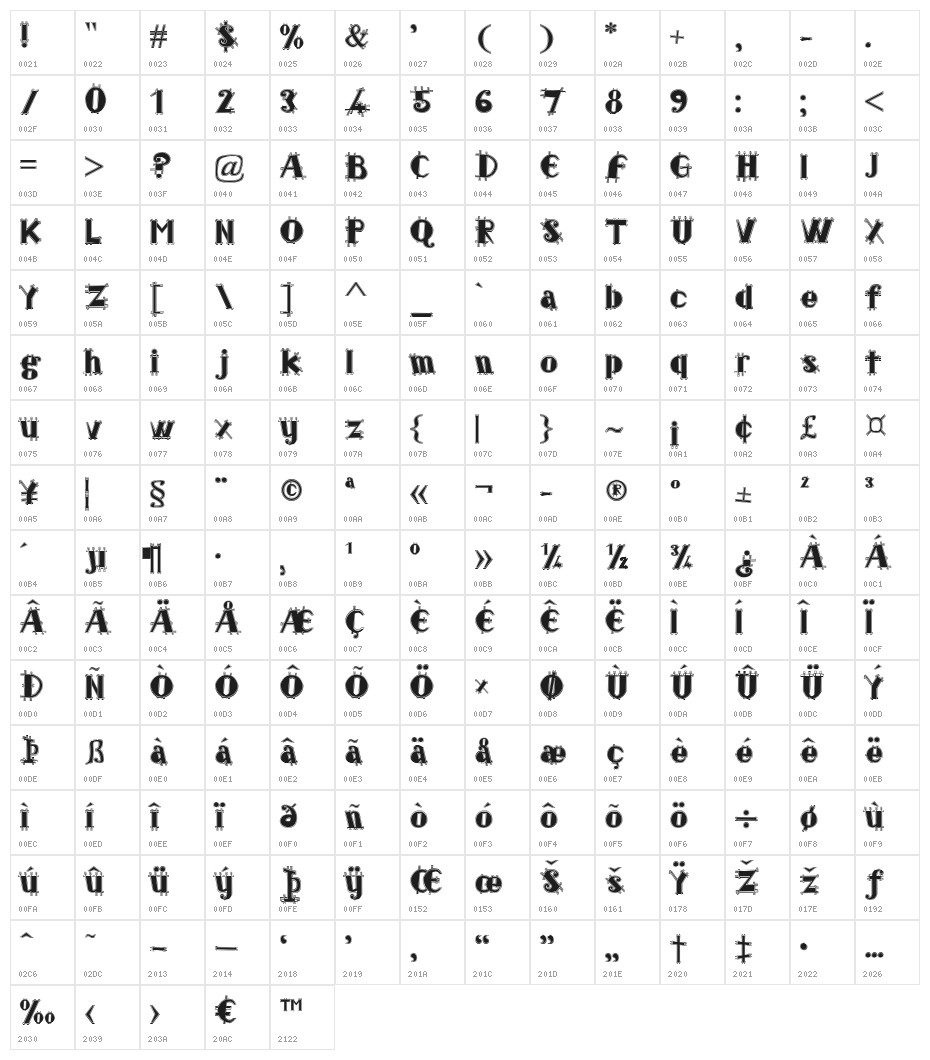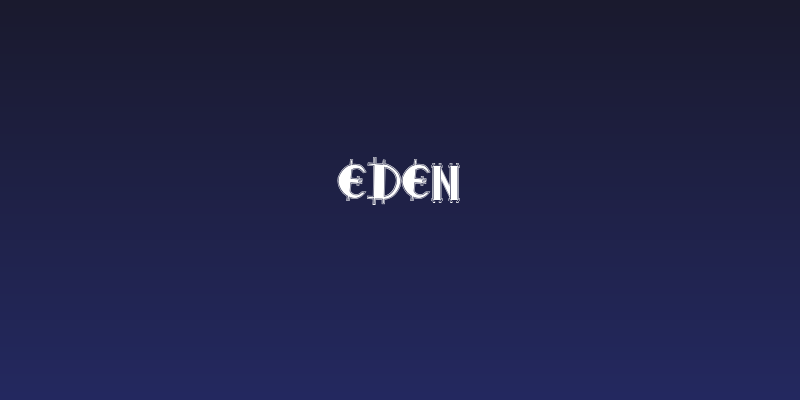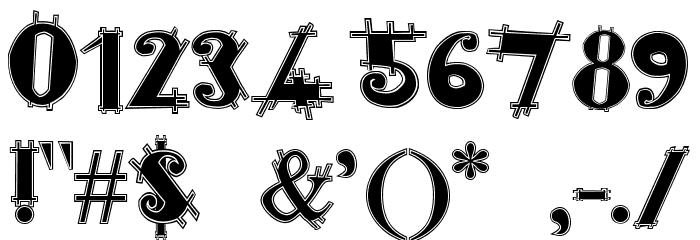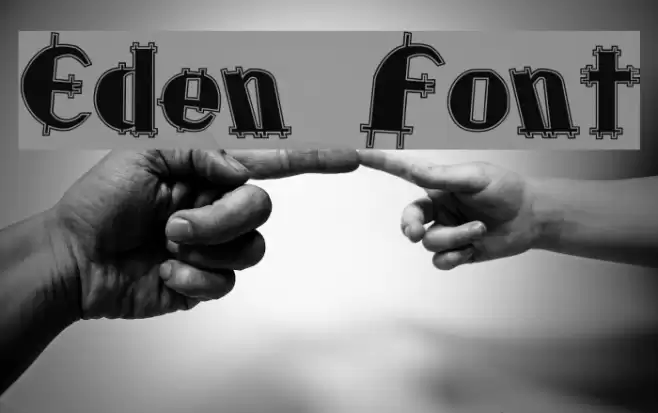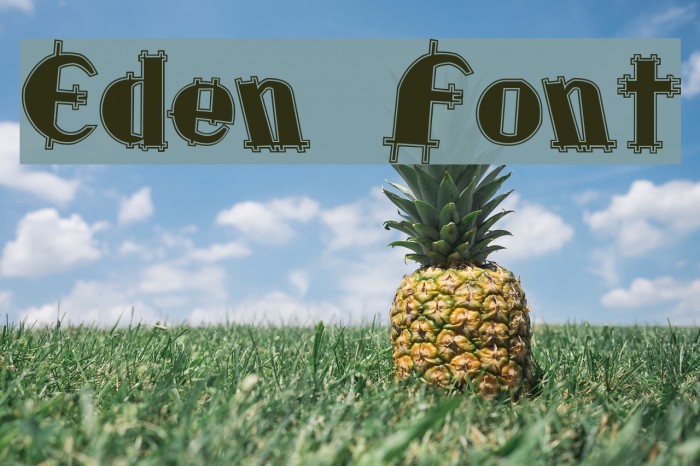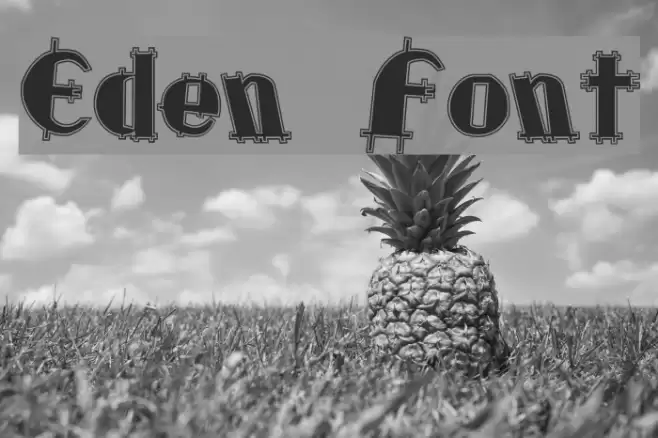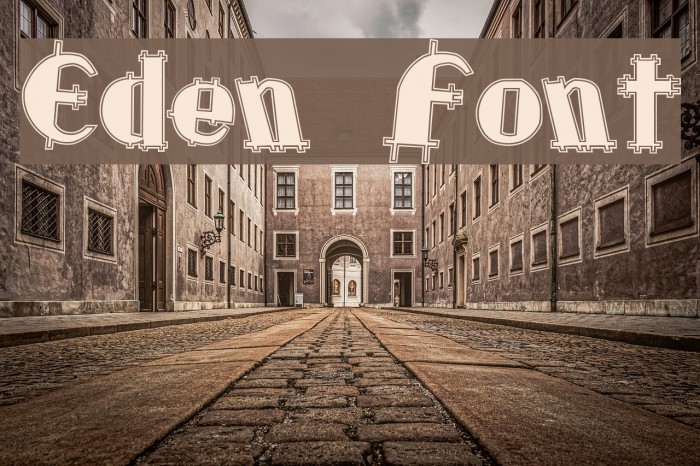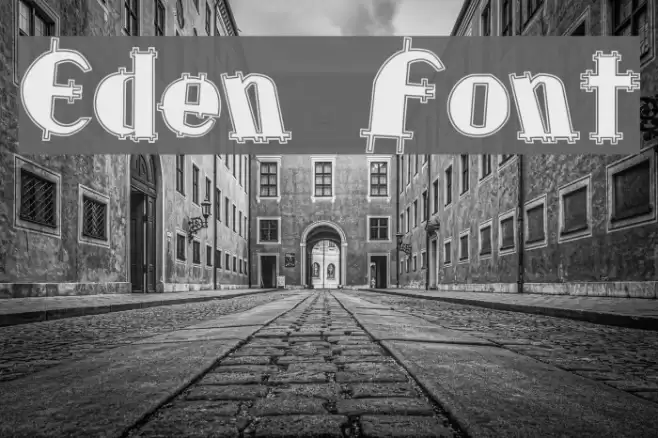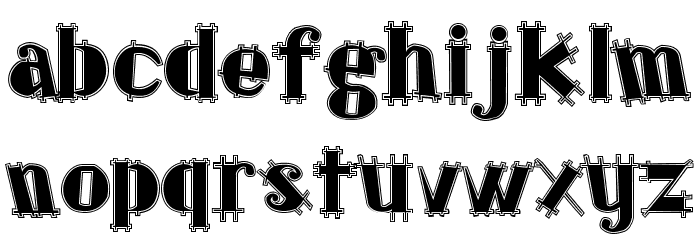
Eden Font
| حالة الاستخدام | Logos, Posters, Creative projects |
| مشاريع مقترحة | Ideal for posters, logos, event invitations, and any project requiring a bold, artistic touch. |